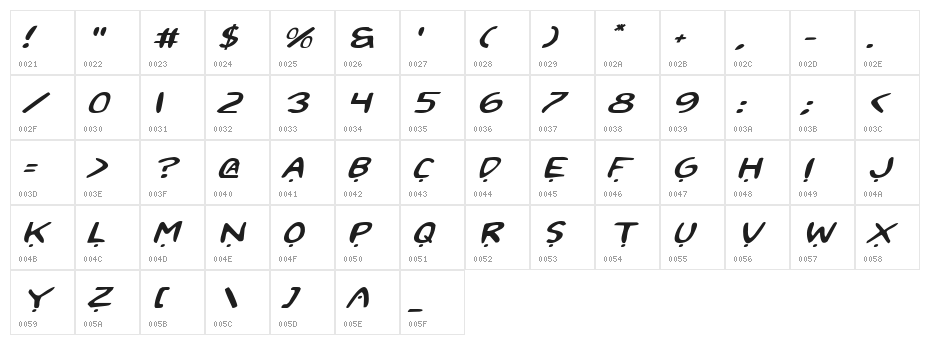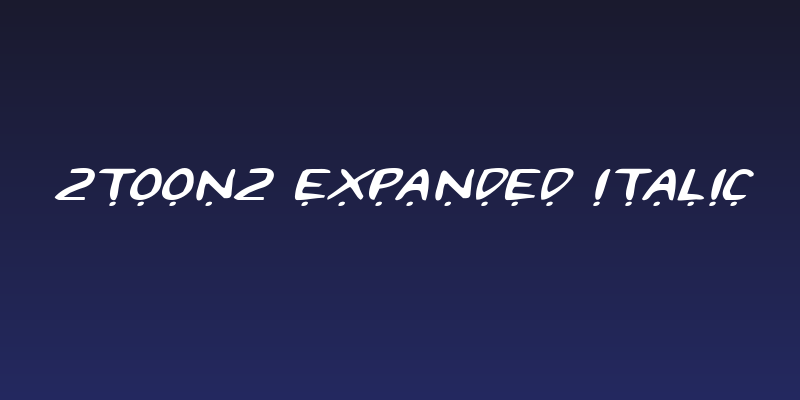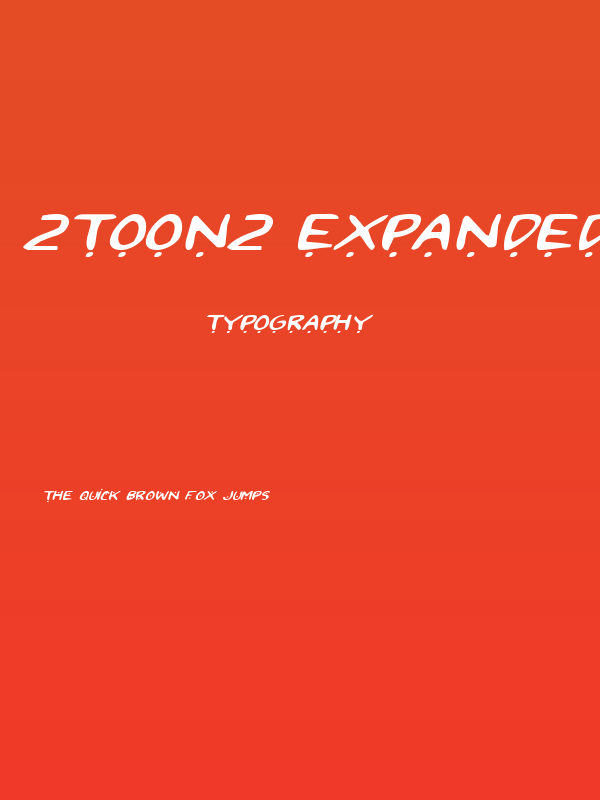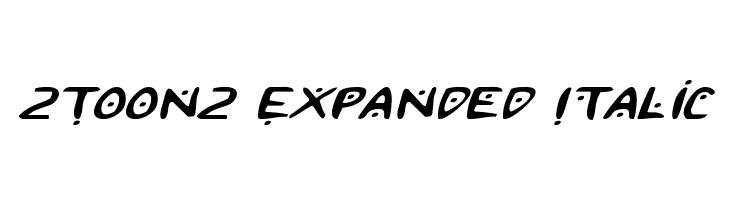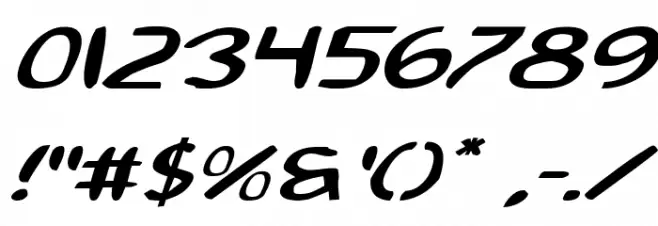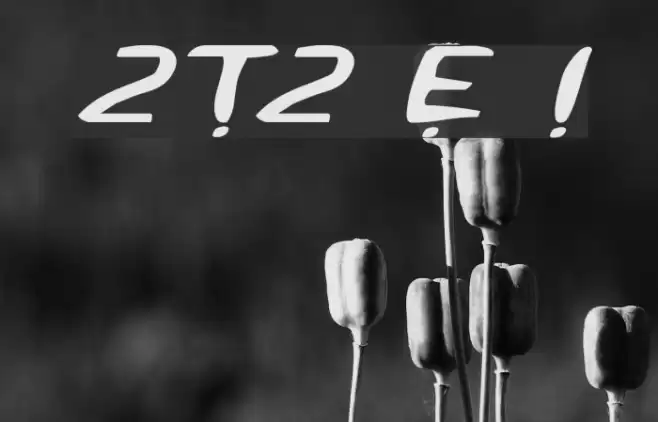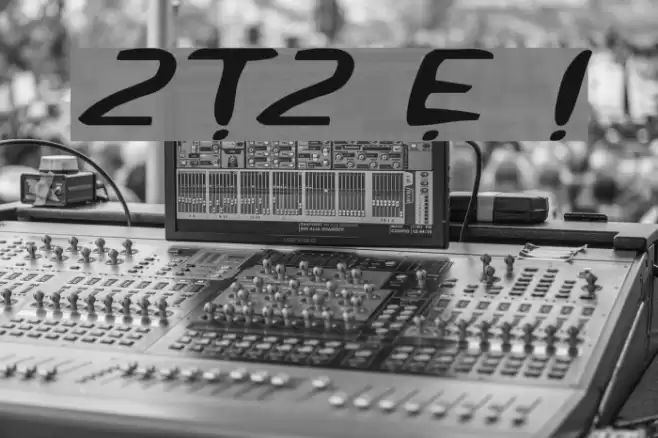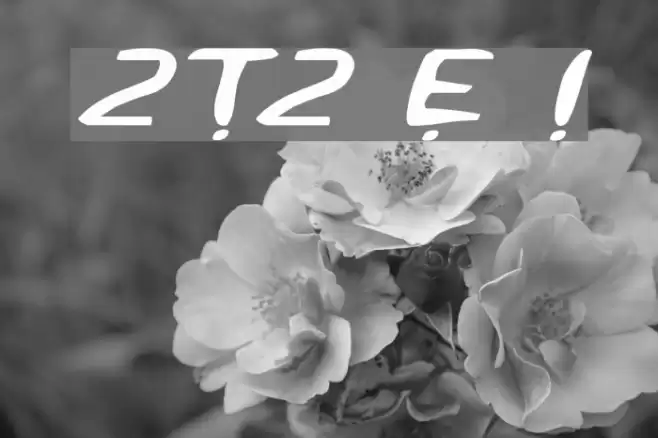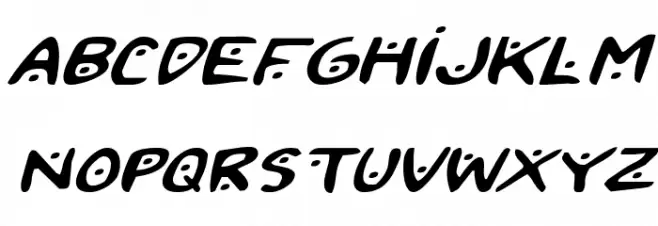
2Toon2 Expanded Italic Font
| النمط العام | Playful, Cartoonish, Energetic |
| مشاريع مقترحة | Ideal for children's books, comic strips, playful branding, and event posters. |